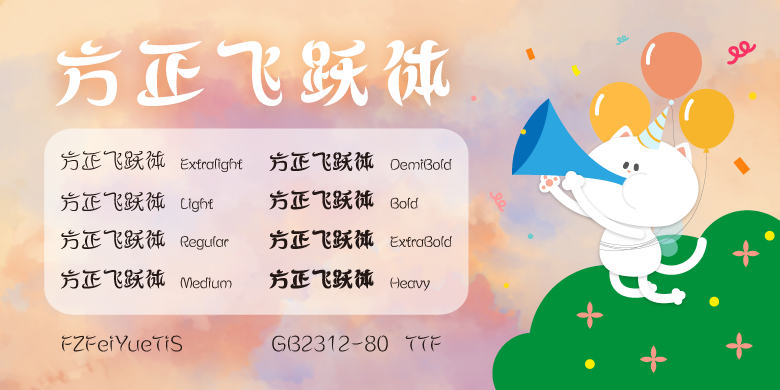
字體介紹:方正飛躍體:壹看這名字感受到活力和跳躍的感覺,設計靈感來源于郭老師在看運動會跨欄賽跑時,發現該名運動員的跑鞋上的標志,立即抓了這條大魚(靈感)。飛躍體的特點是沒有直線,全是弧線組成,橫劃都向右上角斜上,頭部有壹個彎鈎,所有撇,捺,點都用弧線形表達,因此增強飛躍體的感覺,名副其實,飛躍體在設計上突破傳統束縛,並帶來創新悅目的感受,它含有8款粗細,適合年青人的品牌,飲料,體育用品和包裝等廣告宣傳!